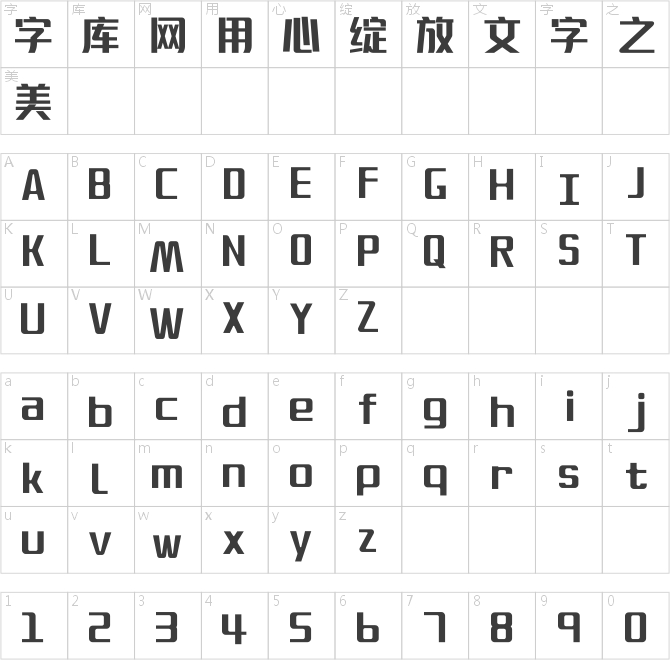
上首銳圓體
上首銳圓體,字體風格銳利偏粗壯,顯得莊重,但卻在轉角處導圓角增添了字體的活躍性,而且字體中有斷開處,使字體顯得生動
上首銳圓體字體字庫是一款讓人賞心悅目、百看不厭的中文字體,適合各類廣告和產品包裝設計應用,字體大小1.85MB,格式為ttf字體,上傳用戶是上首造字,作者/版權方為上首造字